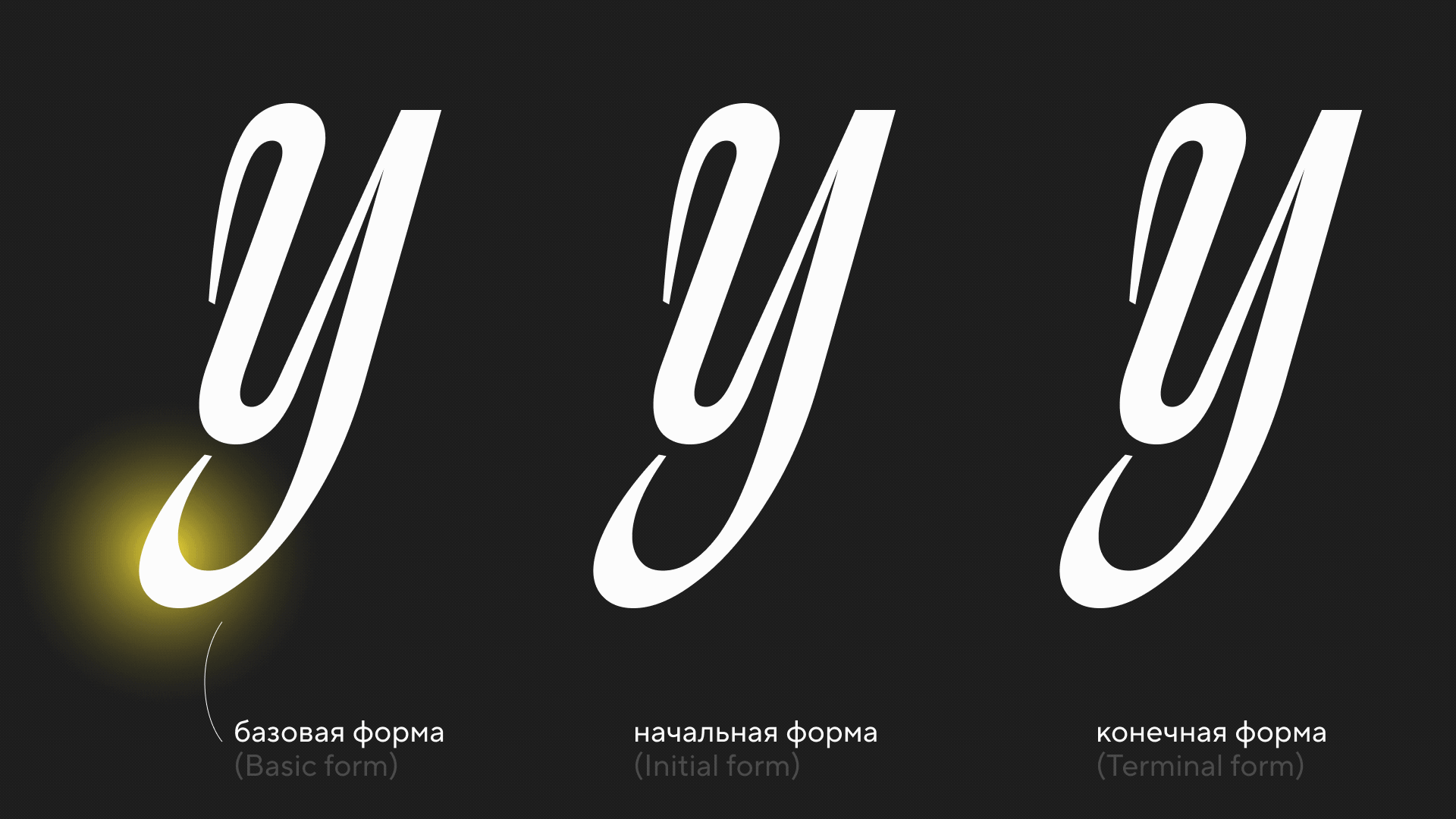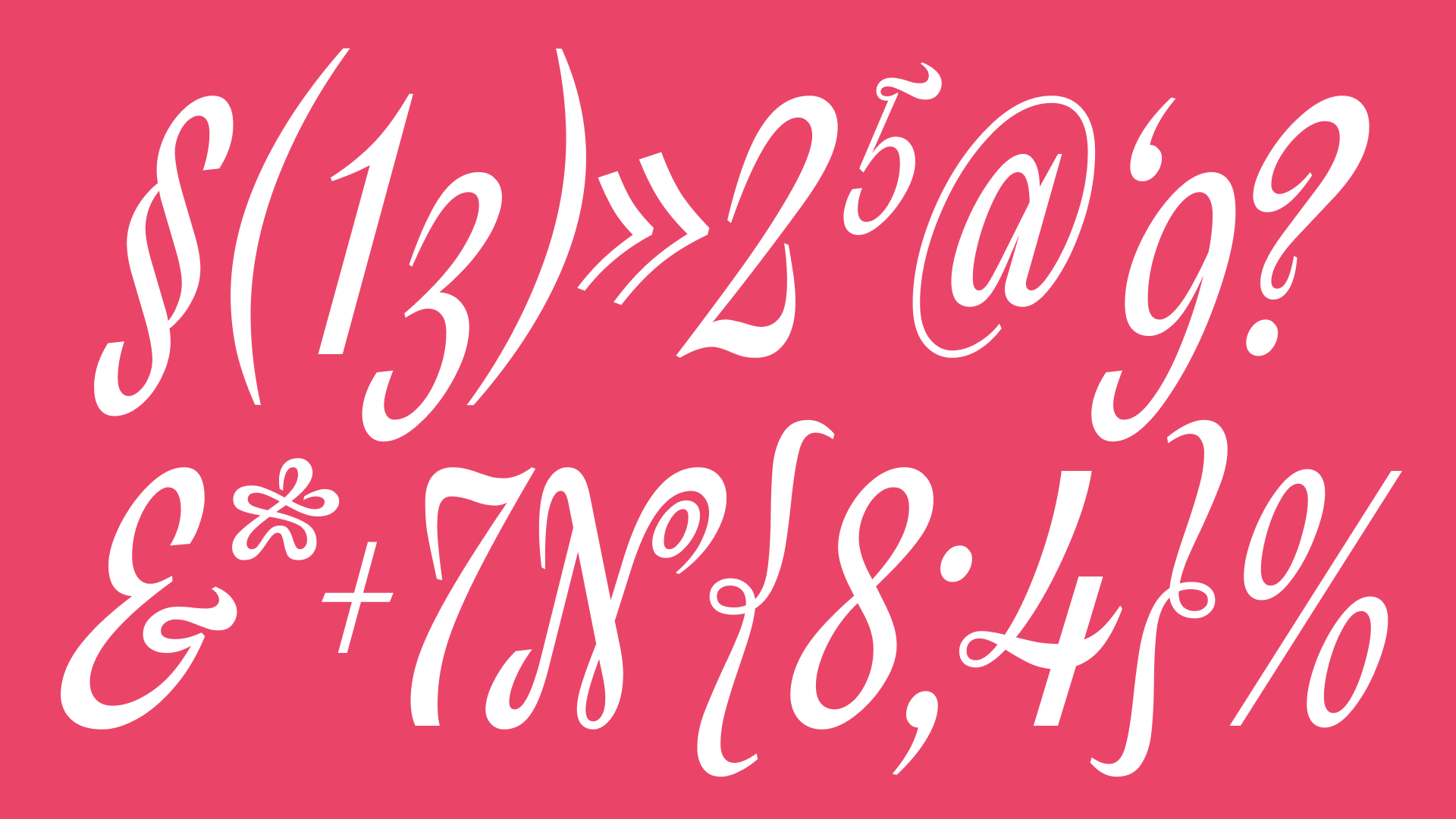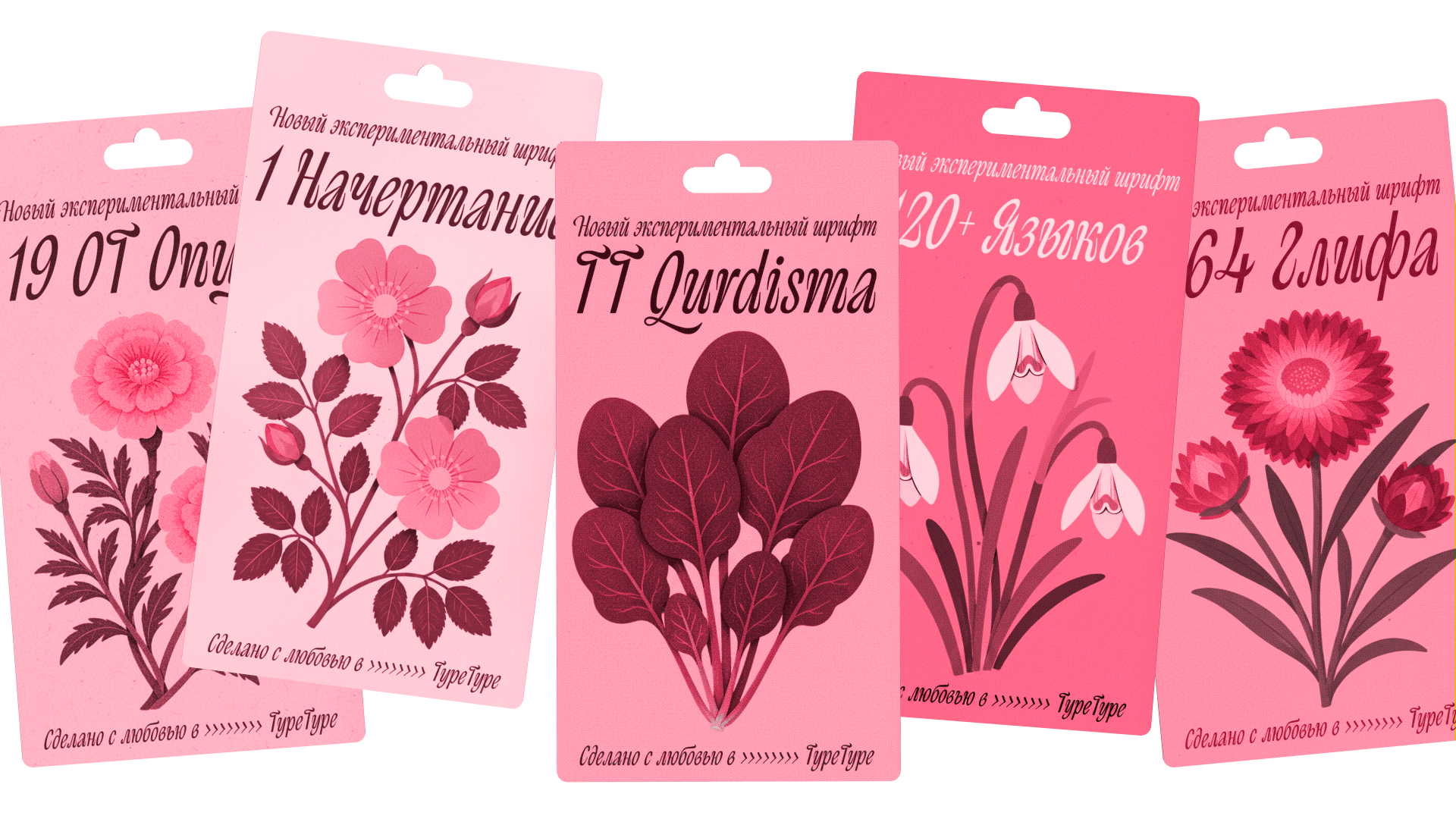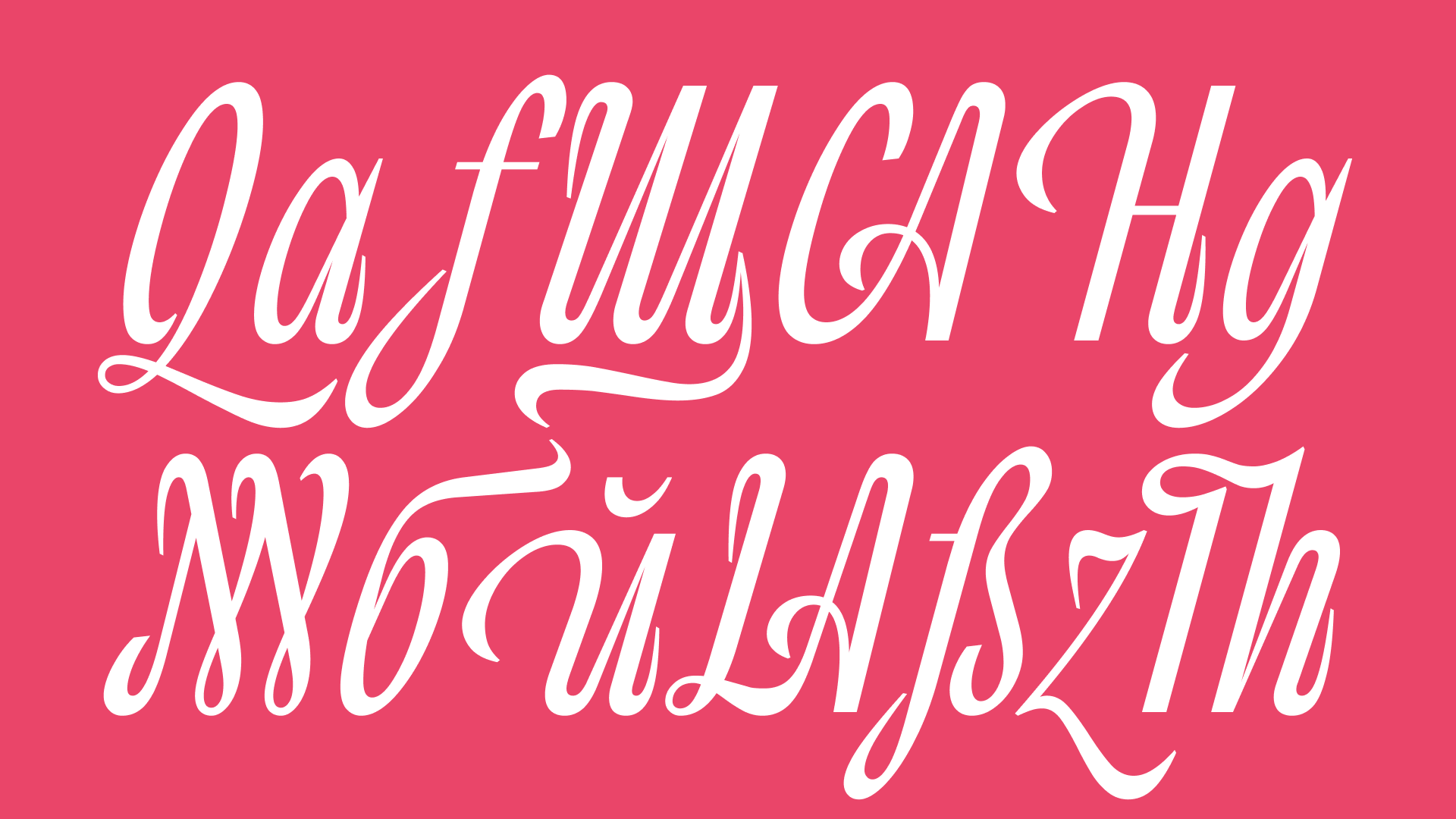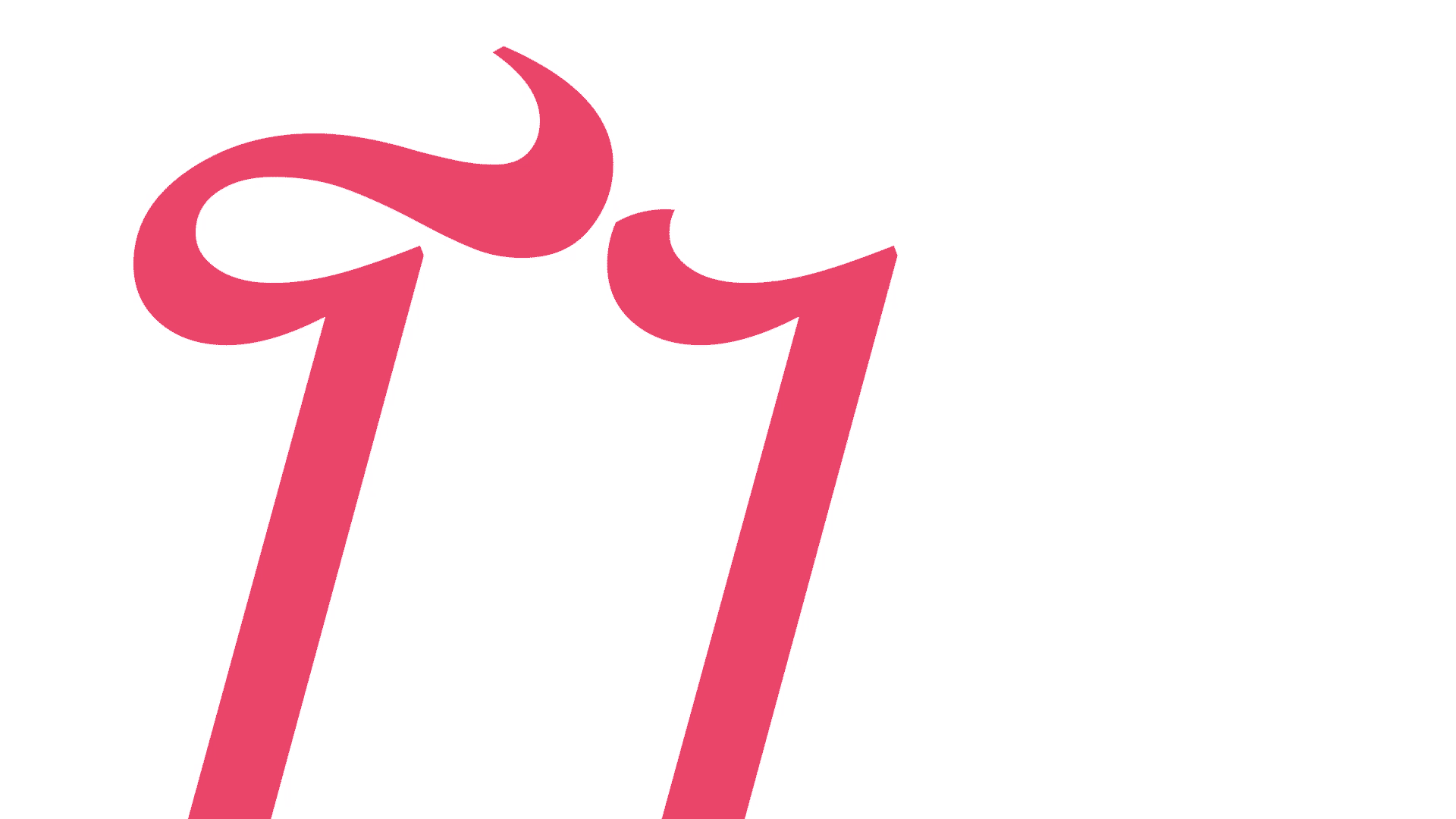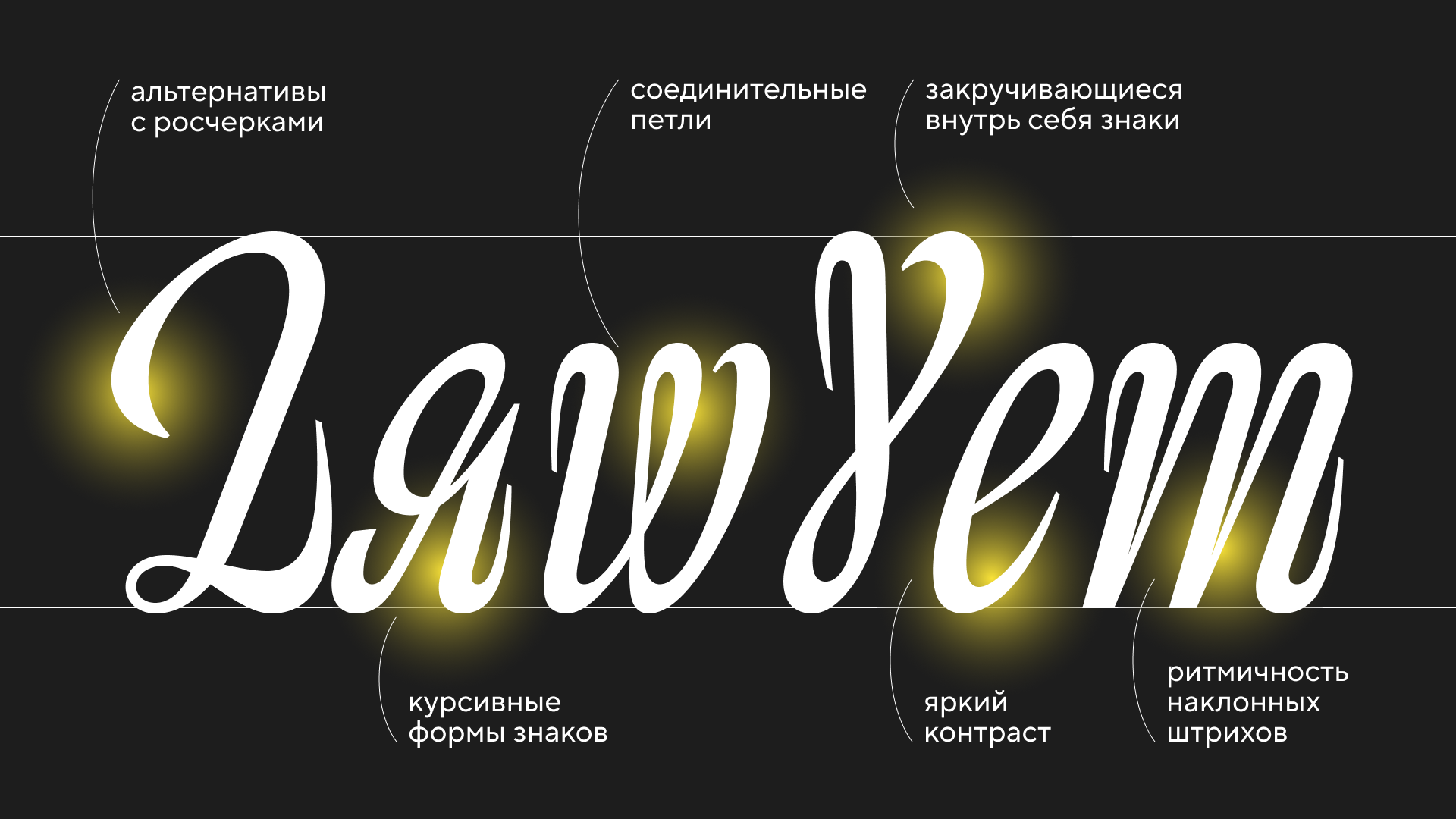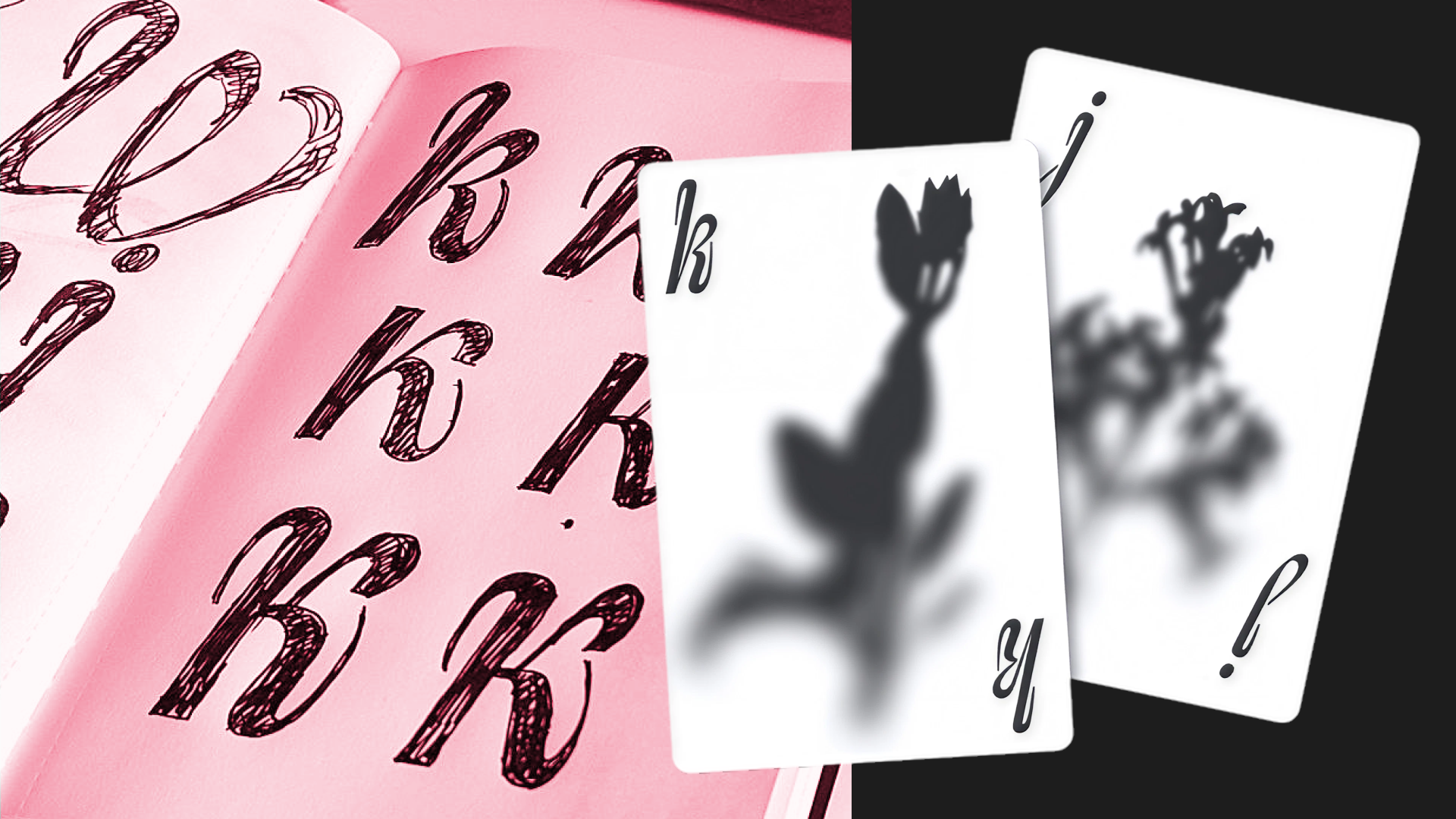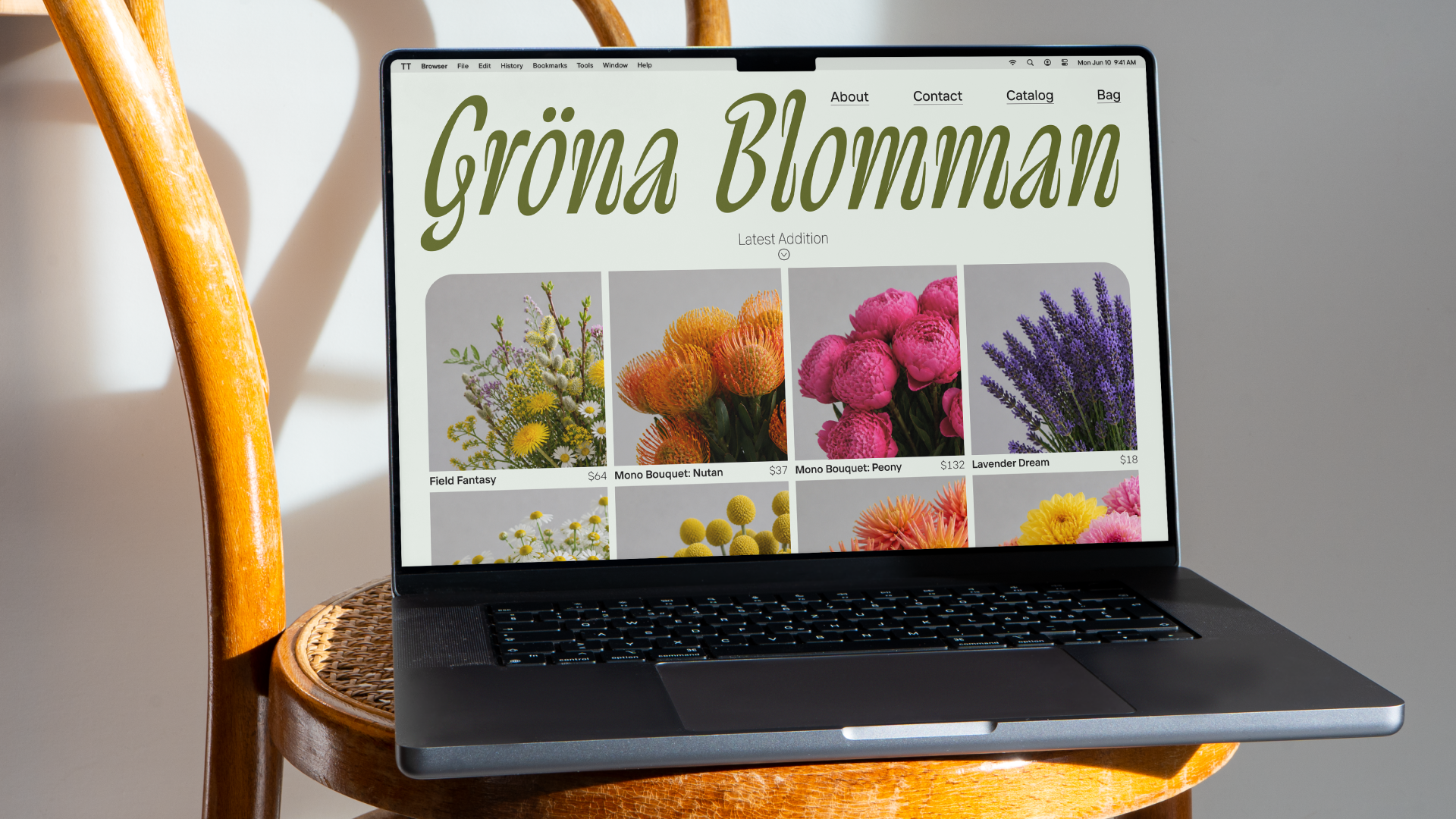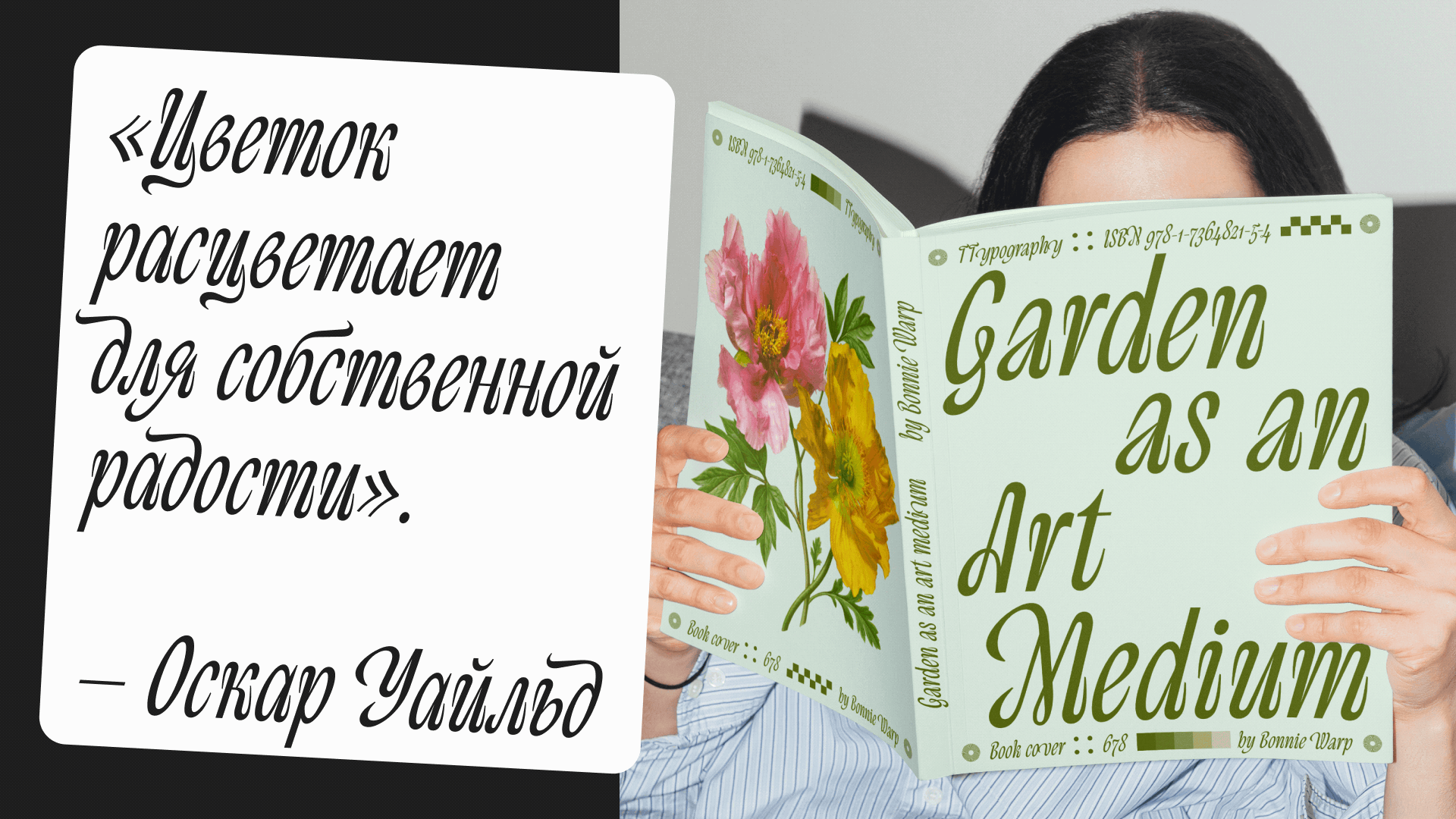
TT Qurdisma
TT Qurdisma — экспериментальный дисплейный шрифт, напоминающий причудливое растение за счёт извилистых и живых линий. В основу эксперимента легла идея смешать в единую концепцию два случайных параметра: «плотный спейсинг» и «настоящий италик». В результате получился шрифт с функциональной кассой и уникальным характером, полный красивых деталей.
Название гарнитуры происходит от греческого κούρδισμα (извилистый). Это узкий, плотный шрифт с закручивающимися внутрь знаками. Его рисунок вдохновлён растениями (водоросли, папоротники, суккуленты). Вьющиеся, плавные контуры рождают растительный орнамент.
Это декоративный шрифт, состоящий из одного наклонного начертания, графика которого отсылает к формам настоящего италика. Он отлично подойдёт для сферы моды, культурных спецпроектов или брендинга.